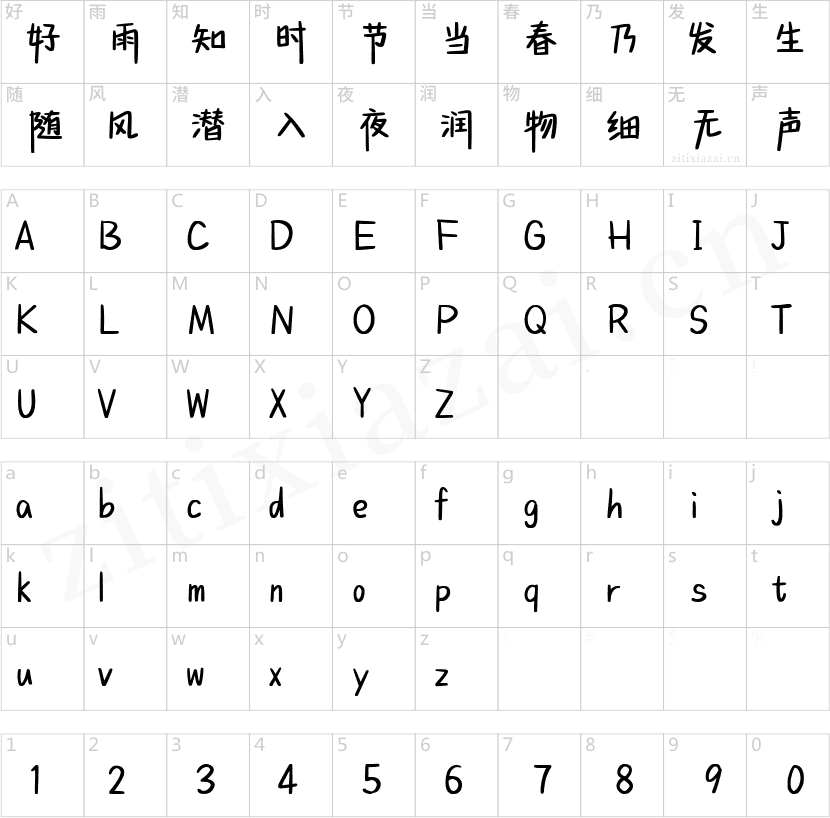
好运藏在努力里
好运藏在努力里字体
好运藏在努力里是一款非常具有艺术性的字体,它的设计灵感来源于对古典艺术的研究,同时又融入了现代字体设计的元素。字形优美,笔画粗细变化自然,给人以大气、典雅的感觉。好运藏在努力里是一款既传统又现代的字体,它的设计充满艺术感,美观大方,实用性也非常强。无论是对于设计师还是对于普通读者来说,都是一种非常不错的字体选择。好运藏在努力里适合用于具有艺术感的场合,比如海报、宣传单张、书籍封面等。由于其字形流畅且具有动态感,也适合用于大量的文本排版,如报纸、杂志等。
- 字体名称:好运藏在努力里
- 字体全名:好运藏在努力里